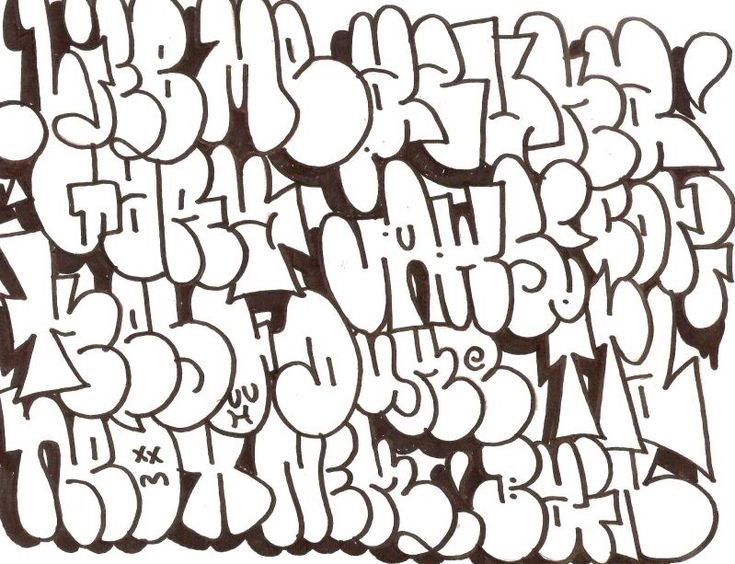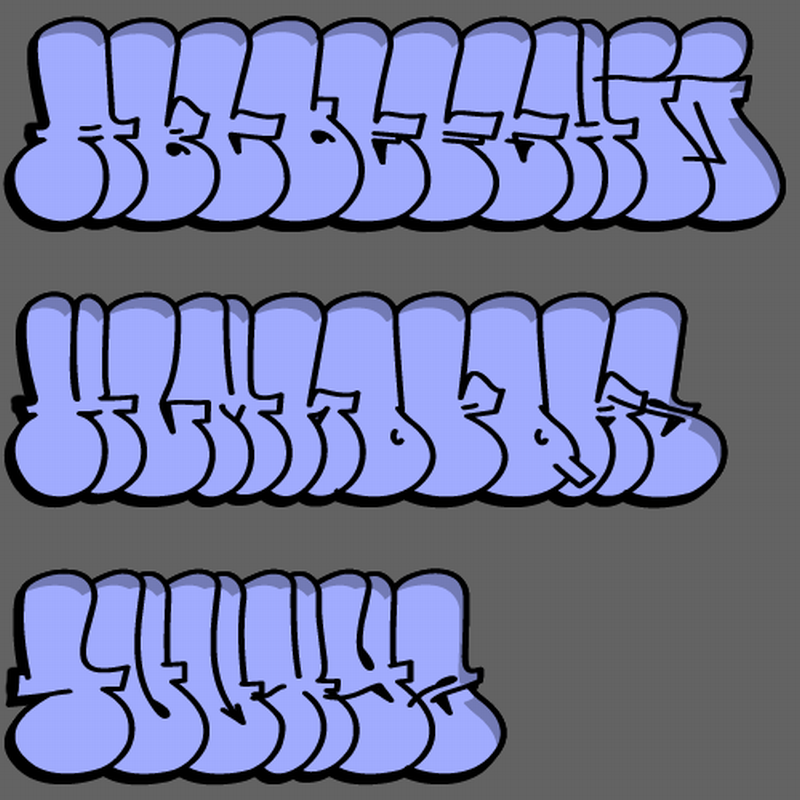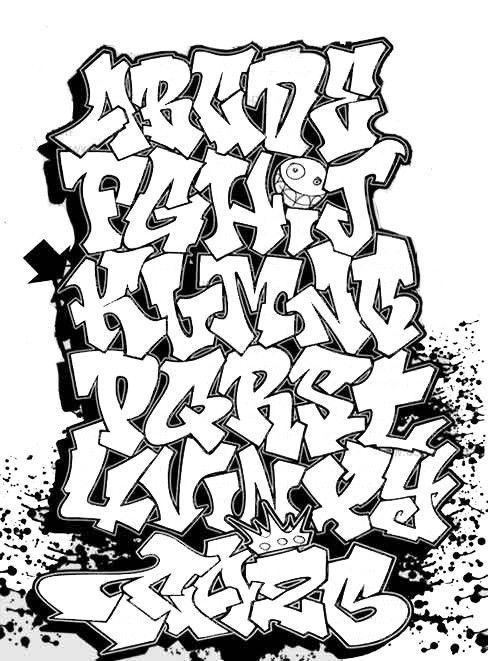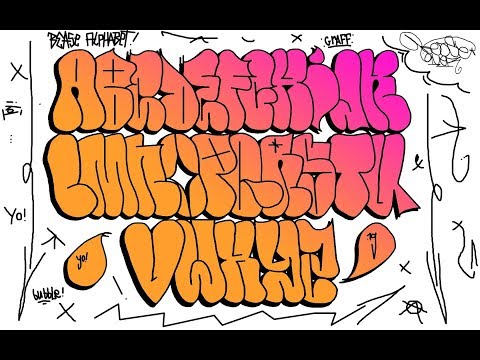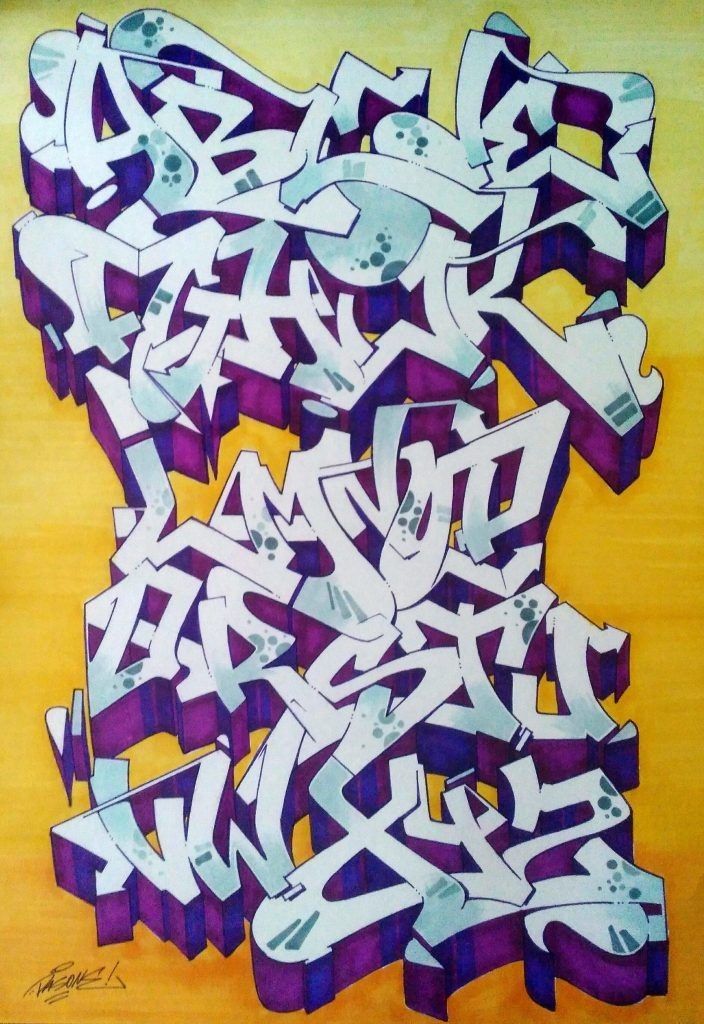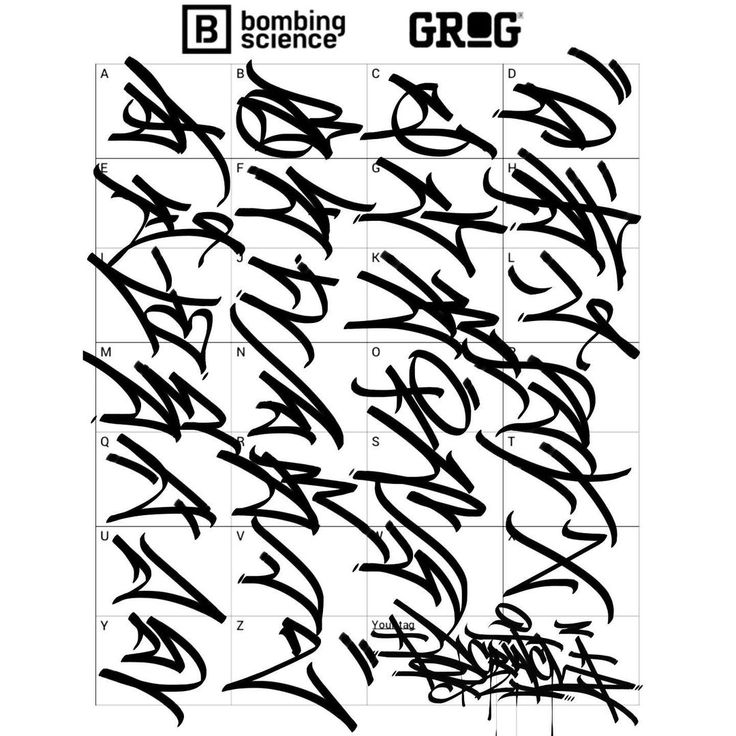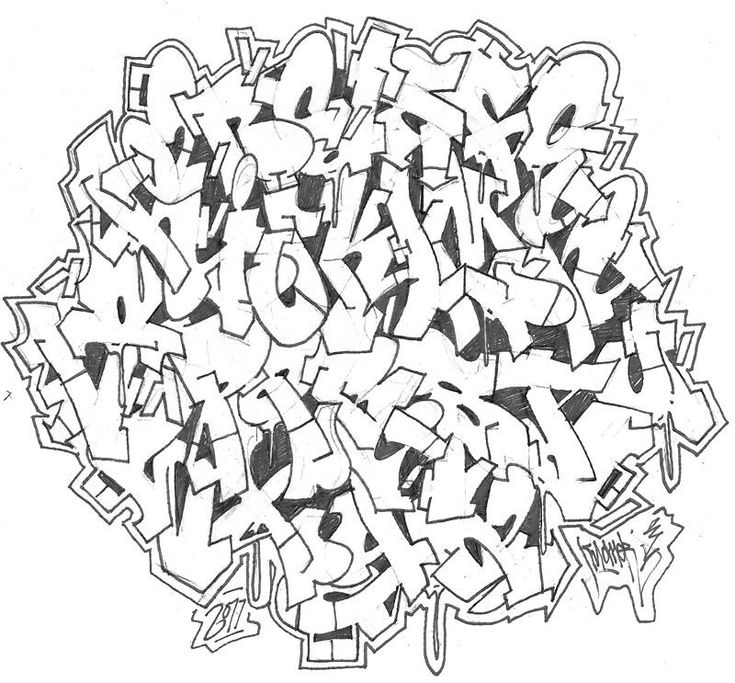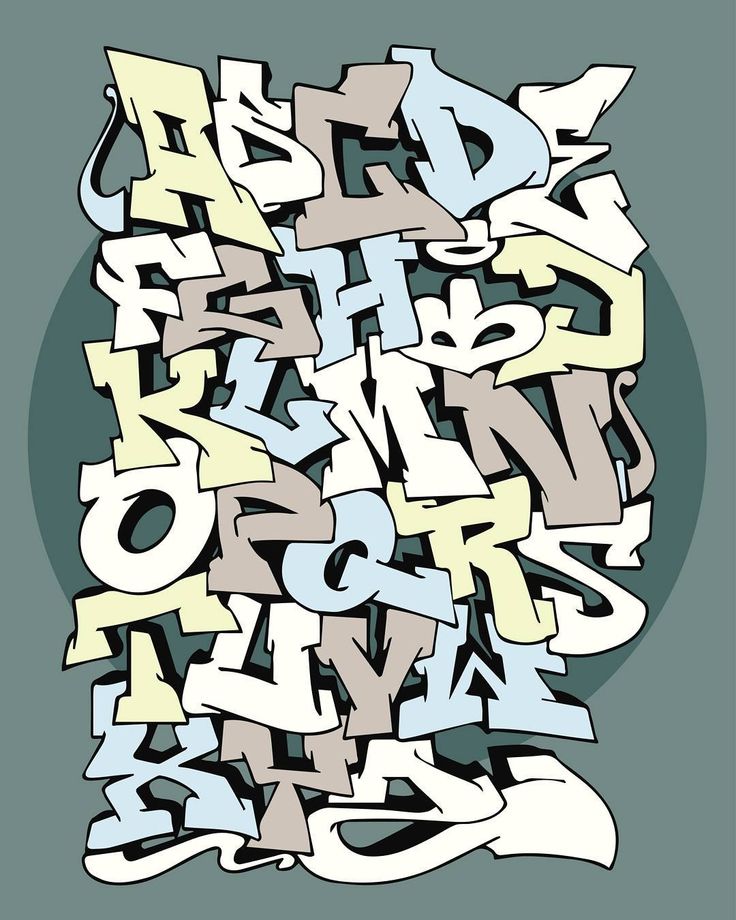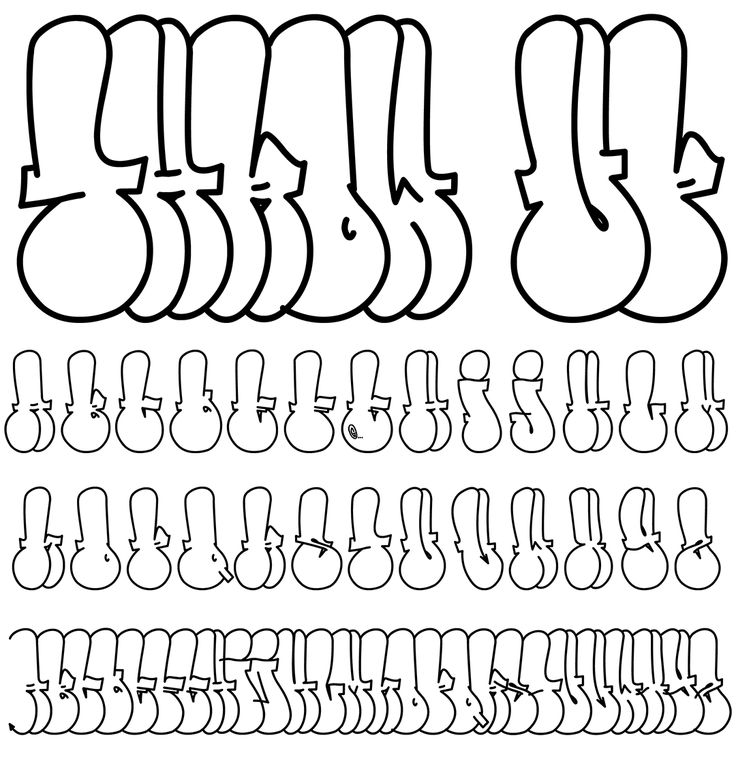
Graffiti is usually appeared as graphics or lettering scratched, scrawled, painted or marked in any manner on property. Graffiti has existed since very ancient times in Ancient Greece and the Roman Empire. In ancient Rome, people don’t have a photocopier or a fax machine or newspaper, and when you have a written message to let other people know, you scratched it on a wall. In modern times, however, graffiti is considered illegal in a lot of countries. But a country that with significant tradition in graffiti is Brazil and Sao Paulo, one of the largest cities in Brazil, is considered to be the current center of inspiration for graffiti artists.
Graffiti can have different styles. Tagging is the simplest type of graffiti, usually done quickly in spray paint, markers or pens and lacking artistic form; A throw-up involves more work than tagging, usually having two or three colors and done in bubble letters; Stenciling can be a quick way to produce more complicated graffiti designs and by using two or more layers, you can produce color-rich designs; Wildstyle is a form of graffiti that was made popular by graffiti artists like Tracy 168, Zephyr in NYC.
Depending on your preferences, there are many fonts that can be used for graffiti purposes such as bubble fonts, stencil fonts , outline fonts etc. However, for complicated graffiti styles, they can never be achieved by fonts. Graffiti fonts can be a good way to study graffiti letters or graffiti alphabet, but you really should learn to express in your style. Get inspired and check out our collection of free graffiti fonts , or use our graffiti text generator below.
Я тоже иногда придумываю свои буквы и зарисовываю их на бумаге, во-первых, чтобы не забыть, а во вторых, воспроизводить на стене знакомый шрифт потом легче, чем изобретать что-то на ходу.
Самые распространенные стили написания и буквы граффити
Баббл
Такие мультяшные объемные буквы – самый распространенный вариант. В шрифте баббл буквы должны сливаться и как бы наплывать друг на друга. Единственный минус – иногда прочитать, что написано в этом стиле довольно трудно, так как буквы могут искажаться практически до неузнаваемости.
Блокбастерс
Для этого стиля граффити нужно сначала нанести на поверхность тон. Лучше сделать это при помощи валика, но можно и баллоном. Это работа не для одного и лучше выполнять ее вместе с товарищами. На фон наносятся ровные и четкие буквы граффити. Многие райтеры используют блокбастерс как свой фирменный стиль.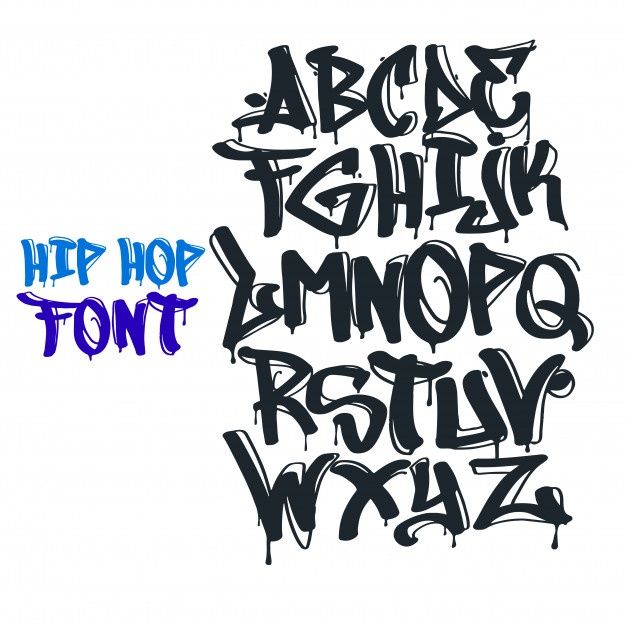
Вайлд
В этом стиле буквы граффити практически невозможно прочитать. Здесь можно проявить фантазию по полной программе. Буквы можно путать, дополнять их любыми элементами и сплетать самым невообразимым образом. Вайлд – довольно сложный авторский шрифт.
FX
Объемный граффити стиль и довольно сложный. Буквы в данном случае требуют тщательной проработки. Не советую новичкам пытаться начинать с него. Все равно ничего дельного не получится.
Мессия
Эти граффити буквы придумали в Америке. Многослойный шрифт с эффектом наложения изображений. Тоже не самый легкий вариант, который используют довольно опытные райтеры. Такие буквы граффити не нарисуешь за 15 минут.
Характер
Это уже даже не буквы, а целая картина. Нарисовать ее можно только при наличии разных насадок. Обычно в характере изображают героев комиксов.